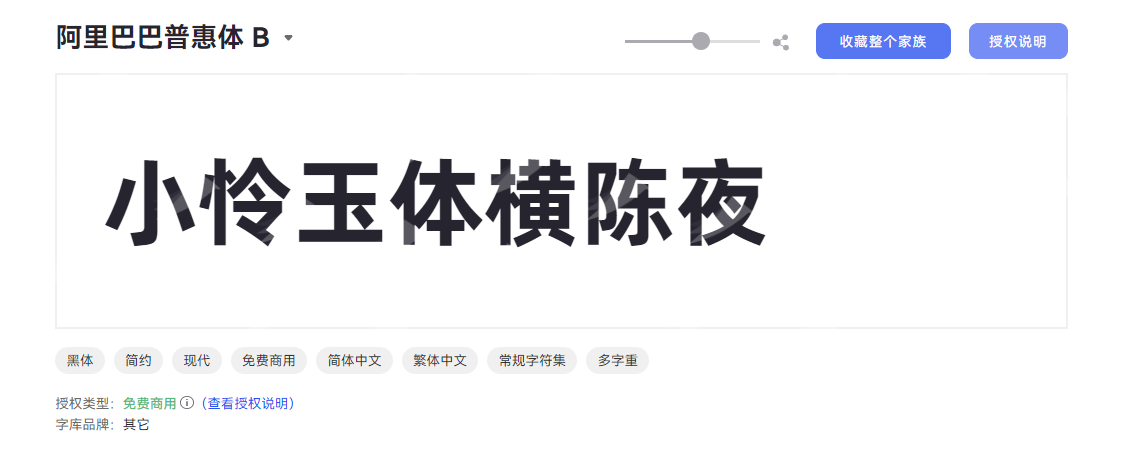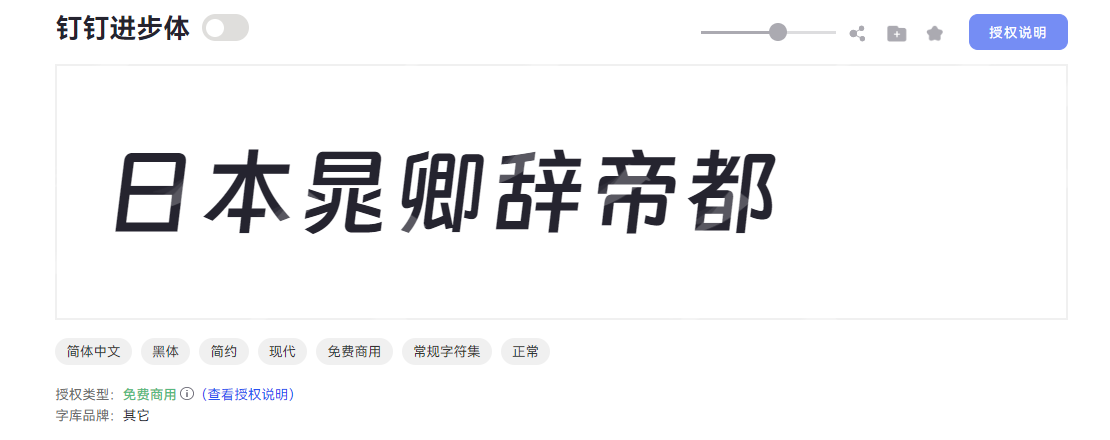
一、现代黑体系列
1.思源黑体
思源黑体是 Adobe 与 Google 联合打造的思源字体家族中的粗体黑体,是很多设计师最常用的字体。作为覆盖多语言的超大字符集字体,思源黑体支持简体中文、繁体中文、日文、韩文、拉丁文、希腊文、西里尔文等 65536 个字形,完全满足跨语言排版需求。
字形方正稳重,字体重心居中,中宫比例适中,既保证了文字的平衡感,又避免了排版时的局促或松散。笔型设计以利落直角为核心,搭配粗体字重与均匀的笔画粗细,方头笔画收尾干净利落,笔画间采用断开连接方式,让整体视觉更显简约干练,适合传递清晰有力的信息。
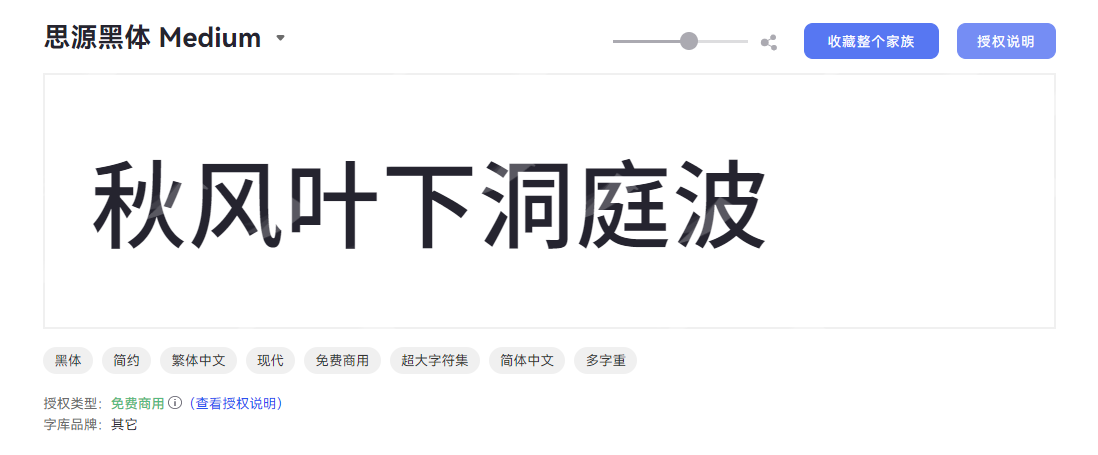
2.阿里巴巴普惠体
阿里巴巴普惠体是 Alibaba 推出的免费商用黑体字体,以现代简约风格成为设计领域的实用选择。
字形方正稳健,重心居中的结构搭配适中中宫,既保证阅读清晰度,又透出利落的现代感。在笔型设计上以直角为主,笔画头部采用方头处理,配合均匀的中等粗细,让字体在视觉上兼具力量感与平衡美;笔画多为断开连接的细节,更添精致层次,避免传统黑体的臃肿感。
3.钉钉进步体
钉钉进步体是由 Alibaba 联合汉仪字库打造的原创黑体字体,以现代简约风格为核心,专为标题与美术字场景设计。
字体结构方正稳健,重心居中且中宫宽博,整体字形舒展大气。笔型融合直角与斜切元素,方头笔画搭配均匀粗线条,既保留黑体的利落质感,又通过笔画断开的细节增添灵动感,让文字兼具力量与韵律。
二、优雅宋体系列
1.字由文艺黑
字由文艺黑是字由品牌推出的创意黑体字体,以现代简约风格为核心,将图形设计法则巧妙融入黑体设计。它的字符集覆盖常规中文,字体兼顾艺术性与实用性,是现代设计中追求文艺感与商业价值的理想选择。
字体字形方正饱满,重心居中且中宫适中,既保留黑体的稳重基调,又通过优雅的艺术弧线处理增强视觉张力。笔型设计独具特色,以利落直角勾勒轮廓,搭配方头笔画与均匀粗细,笔画连接采用断开处理,既保持线条的独立性,又让字形更显灵动透气。
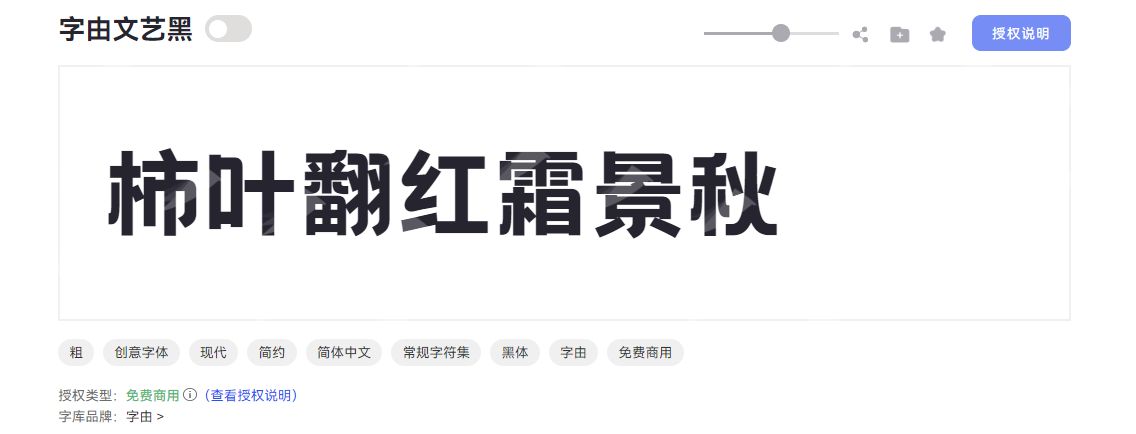
2.优设标题黑 免费商用的力量感创意字体
优设标题黑是优设字库旗下一款极具现代张力的创意字体,凭借其独特的力量感与现代美学,为设计作品注入鲜明个性,是免费商用领域中兼具实用性与设计感的优质选择。
字形方正稳健,重心居中的设计让字体视觉平衡感十足,中宫适中的结构既保证了文字的紧凑性,阅读体验清晰舒适。笔画多采用利落直角,线条硬朗有力,搭配方头收尾与断开连接的细节处理,既保留了黑体的庄重感,又通过几何化的笔触增强了现代科技感。字重“粗”且粗细均匀的特性,让字体在标题场景中极具冲击力,轻松抓住视觉焦点。
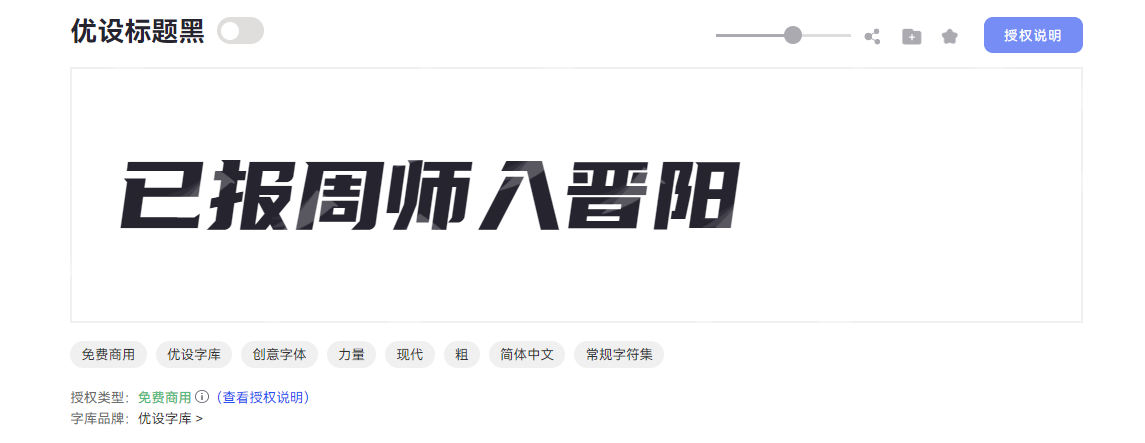
三、传统书法与创意体系列
1.站酷庆科黄油体
站酷庆科黄油体是由站酷字体推出的创意简体中文字体,以现代简约风格为核心,兼具端庄优雅的视觉气质。常规字符集覆盖日常设计需求,既能传递活泼亲和力,又不失现代设计的高级感。
字体采用方正结构设计,字体重心居中,中宫松紧适中。笔画以粗线条为基调,末端融入圆润处理,搭配均匀的粗细分布与圆头笔型设计,既保留了几何图形的利落感,又通过断开式笔画连接增添灵动气息,恰似黄油般柔滑醇厚的质感,为创意作品注入独特视觉魅力。
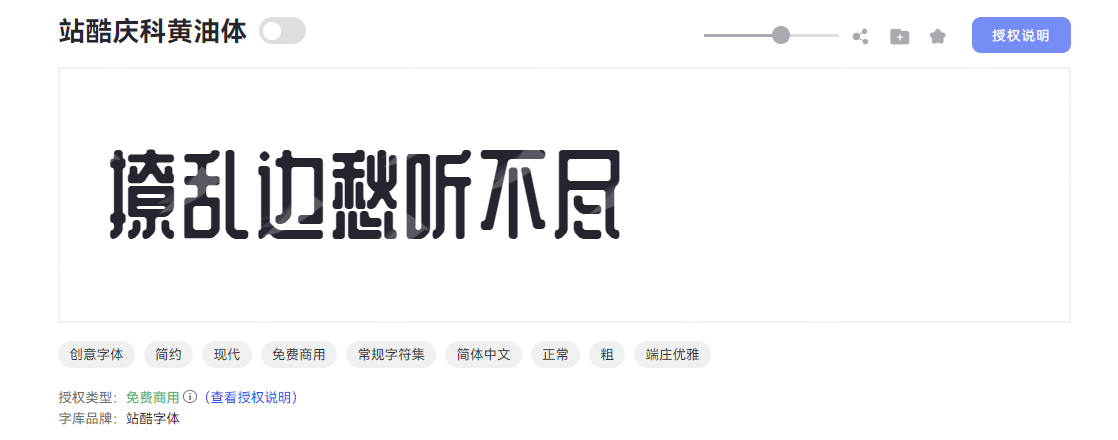
2.斗鱼追光体
斗鱼追光体是一款由斗鱼武汉研发部 UED 指导、品牌组设计成员主导打造的现代创意字体,兼具品牌基因与设计巧思,成为现代设计中兼具颜值与性价比的优选字体。
字形方正大气,重心居中,字重饱满粗壮,笔画粗细均匀,方头笔画的利落感与独特的斜切笔型形成鲜明对比,局部笔画更融入精致装饰元素,搭配断开式的笔画连接方式,既保留了现代字体的简洁利落,又展现出创意字体的灵动张力。
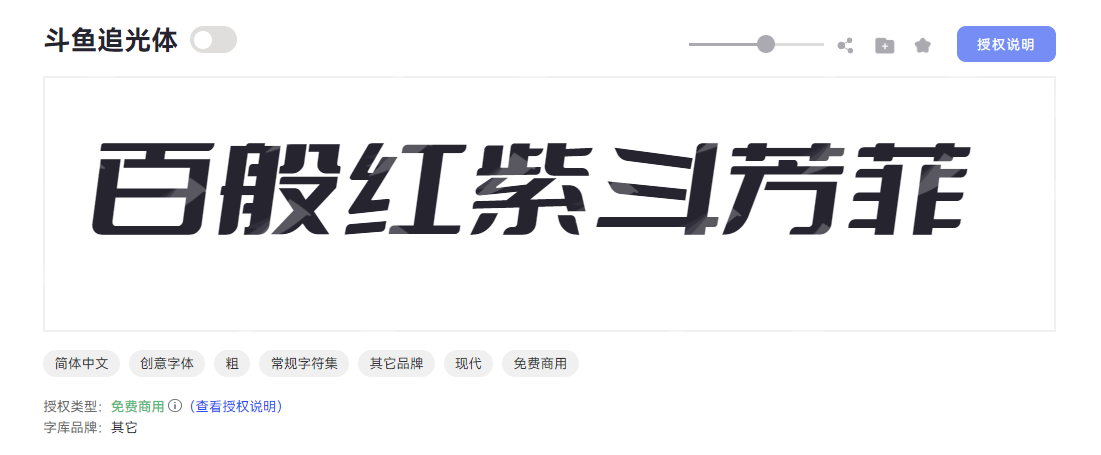
3.江西拙楷
江西拙楷是一款充满古韵的中国风楷体字体,由设计师黄煜臣精心打造,旨在传承传统书法美学,同时兼顾数字时代的阅读体验。该字体将古典美学与现代设计需求巧妙融合,让每一个文字都散发着沉静典雅的东方韵味。
字体采用方正稳健的字形结构,重心居中且中宫松紧适度,展现出楷书特有的端庄气质。其方头笔画搭配均匀的线条粗细,融入传统书法的装饰性笔触,既保留楷书的端庄大气,又通过断开的笔画设计增添古朴拙趣。